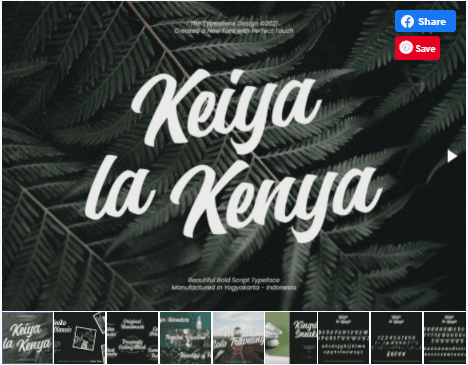
Keiya La Kenya Font
Keiya La Kenya - это великолепный и смелый рукописный шрифт, созданный для придания вашим заголовкам и проектам логотипов нотки ретро. Этот шрифт выглядит сильным, уверенным и динамичным и может добавить ностальгический характер вашему дизайну.